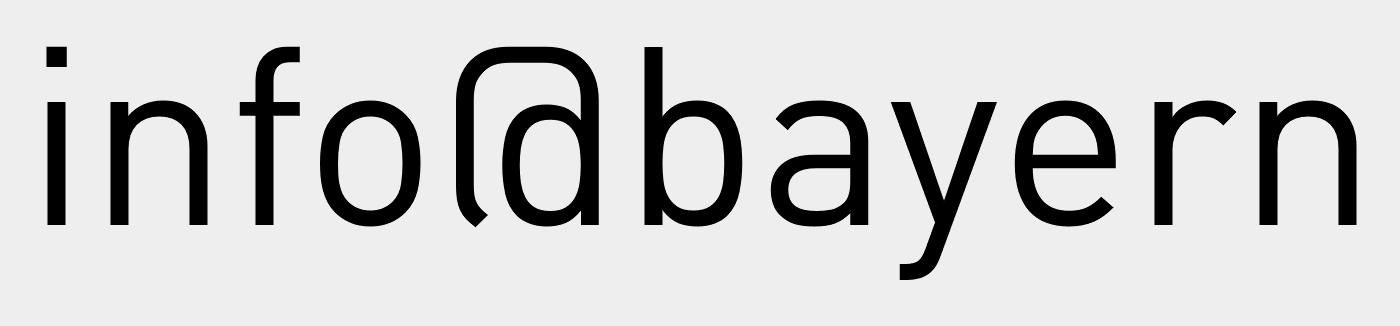
Hat die DIN Pro ein alternatives @-Zeichen?
Das originale @ ist  ja eher nicht zu gebrauchen – der Kunde fragt zu Recht, warum da "infoldbayern" steht – mit ld-Ligatur:
Gibt es eine gute Alternative?
Ah, vielen Dank! SS4 hat meine DIN Pro nicht, aber im SS1 ist ein "normales" @ enthalten.
Zusatzfrage: Wie kann ich denn ein komplettes Dokument in SS1 ändern? Es sind leider keine Formate angelegt …
Zuerst das Zeichen markieren und über die Zeichenpalette und die OpenType-Option den passenden Formatsatz zuweisen. Damit ein Zeichenformat erstellen. Dann im Suchen-Dialog unter GREP das Zeichen im Suchen- und im Ersetzen-Feld eingeben und unten das neu angelegte Zeichenformat zuweisen.
Alternativ auch über suchen/ersetzen und dort dann im glyphen-reiter. So lässt sich das normale durch die Sonderform ersetzen.
(Wir haben in allen DIN-Pro-Dokumenten im grundlegendsten aller Absatzformate das bessere @ per Opentype-Schalter aktiviert ... Und es steht mit auf der Checkliste für den Datenausgang, damit diese Monstrosität nie (mehr) raus geht. Dafür sehen wir daran auch immer gleich, wenn die Kunden-Hausgrafik was nebenher selbst gemacht hat ...)